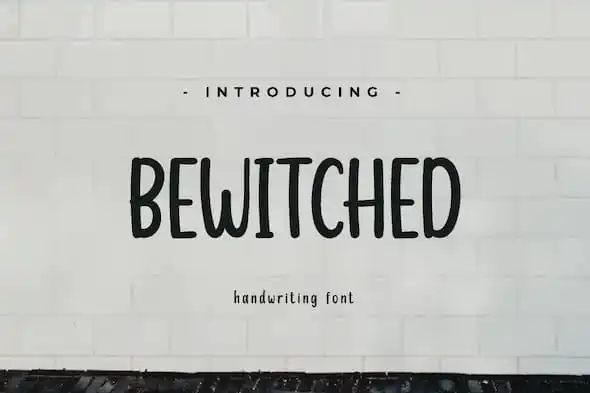
Bewitched Script Font – Fonte Grátis
Bewitched Script Font
Bewitched Script Font é uma fonte de escrita à mão que transmite uma sensação única, perfeita para adicionar um toque elegante e memorável a seus designs digitais. Com sua aparência quase mágica e deslumbrante, esta fonte garante que seu público sempre se lembre do recado em cada projeto. Ideal para ambientes corporativos ou pessoais onde o impacto inicial é crucial, essa fonte de escrita à mão oferece uma maneira criativa de fazer sua marca realmente brilhar. Seja você um designer gráfico experiente ou um iniciante que busca adicionar um toque diferente e memorável a seus trabalhos, Bewitched Script Font está aqui para ajudar a tornar sua obra de arte digital ainda mais especial.